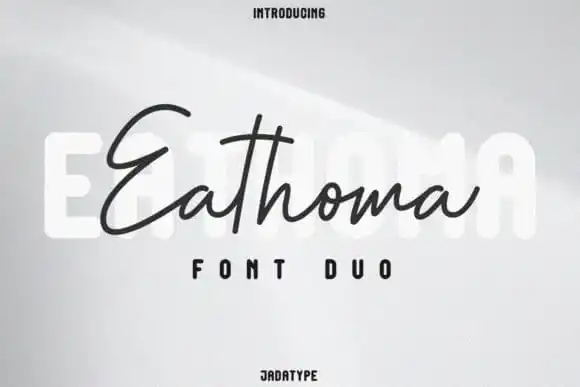
Eathoma Handwritten Font Duo – Download Grátis
Eathoma Handwritten Font é uma elegante escolha para quem busca uma mão-dilatada para escrita que transmite serenidade e delicadeza. Desenvolvida pelo designer jadatype na categoria de Fonts Script, essa font oferece um conjunto completo de letras maiúsculas e minúsculas com números internacionais, todos elaborados a mão. Suas letras são verdadeiramente escritas à mão, com o estilo realista que as torna perfeitas para adicionar uma nota romântica e personalizada em cartões de casamento, convites ou qualquer projeto gráfico. Além disso, Eathoma Handwritten Font oferece duas variantes: um tipo sans serif e outro do tipo escrita à mão. Ambas as variações são sutis e leves, criando uma dupla que combina a delicadeza do handwritten com o estilo limpo da sans serif. Esta fonte é ideal para qualquer projeto que precise de uma toque romântico e pessoalizado. Com Eathoma Handwritten Font Duo na sua coleção, você pode garantir um gráfico elegante e sofisticado que captura a essência do amor em cartões, convites e outros projetos gráficos.